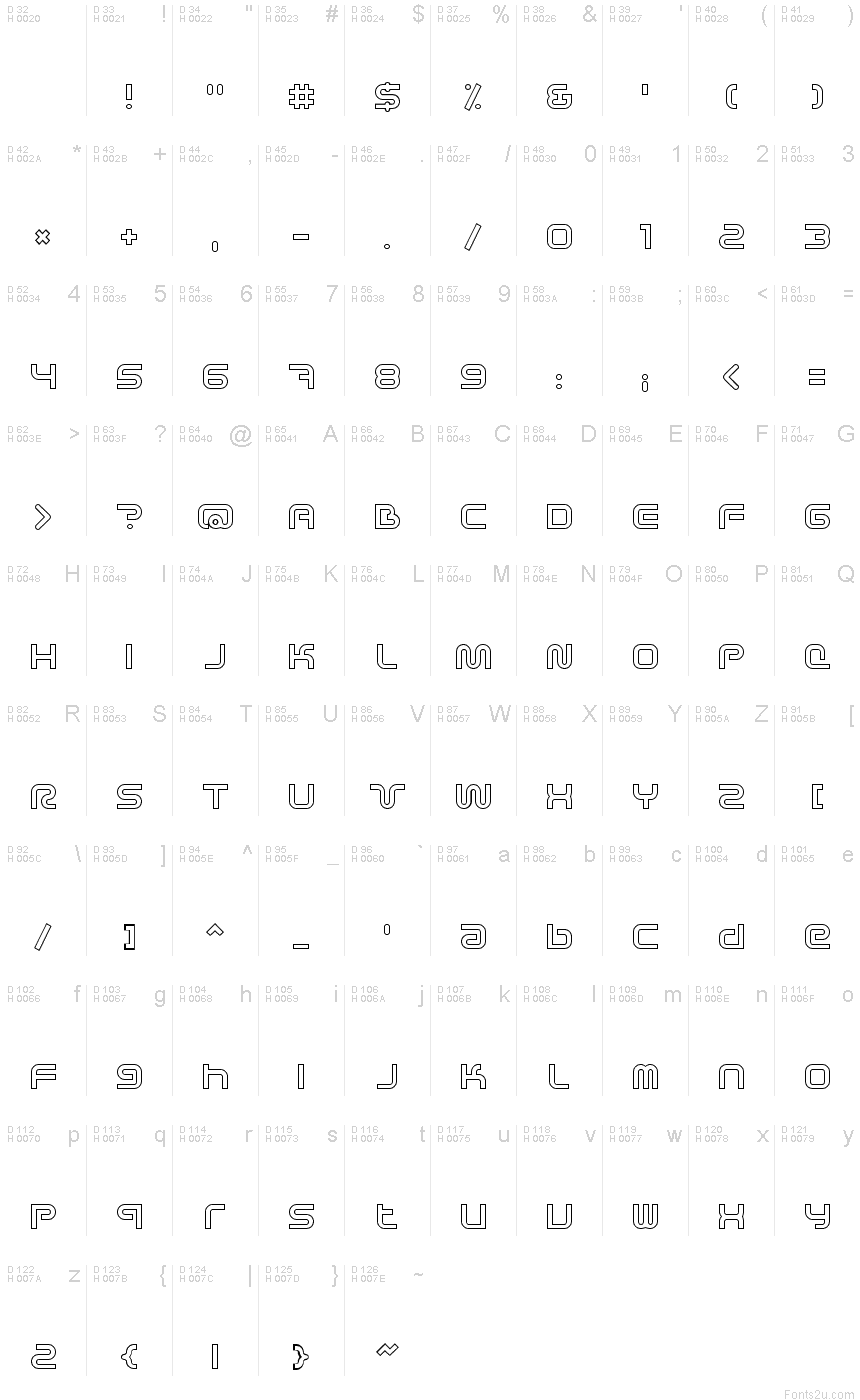
Sci Fied X Outline, di dustBUST Fonts, è un font display futuristico e gratuito dal design a contorno, con maiuscole tubolari morbide e un elegante mood retro-sci-fi. Le lettere presentano angoli lunghi e arrotondati e tratti a doppia linea, conferendo al font un aspetto pulito che ricorda i pannelli di controllo, evocando più l'era spaziale che uno stile industriale.
Si adatta perfettamente a titoli di poster, loghi di giochi, copertine synthwave, grafiche per eventi tecnologici e cartelli di titoli, dove un font gratuito deve trasmettere un forte richiamo temporale senza bisogno di ulteriori stilizzazioni. Poiché le maiuscole sono ampie, aperte e costruite con percorsi di contorno continui, funziona molto bene anche per titoli brevi e monogrammi che desiderano una presenza leggera e sospesa.